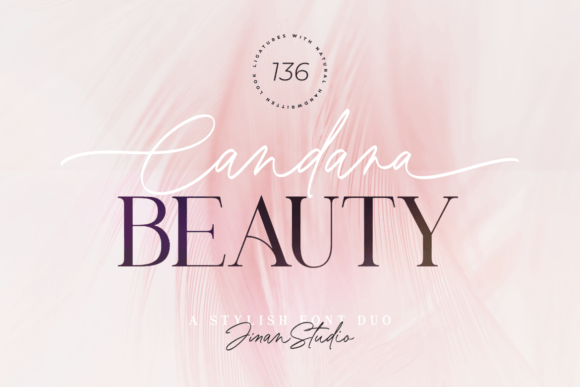
Candara Beauty Duo
Doğru tasarım öğelerini bulmak zor olabilir, ancak Candara Beauty Duo, çalışmanızı anında bir üst seviyeye taşıyan olağanüstü bir koleksiyon sunar.
İster İsteğe Bağlı Baskı (POD) ürünleri, ister düğün davetiyeleri veya sosyal medya grafikleri oluşturuyor olun, Candara Beauty Duo ideal bir uyumdur.